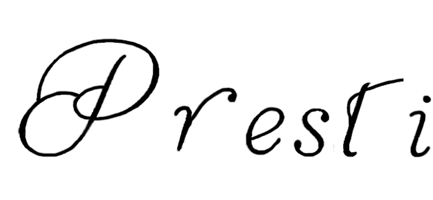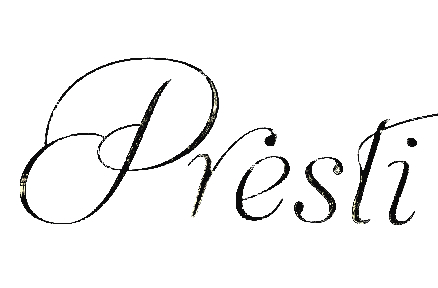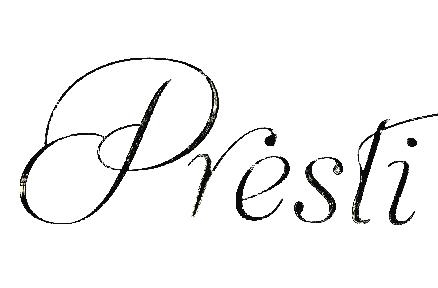
Bitte sagt mir, welche Schrift das sein könnte
ich habe vieles im Netz gefunden, aber eben nicht genau diese Art Schrift.
Kann mir jemand helfen?
[…] ich habe vieles im Netz gefunden, aber eben nicht genau diese Art Schrift.
Moin, sei mir nicht böse, aber Du hast völlig verkehrt gesucht.
Gerade bei verschlungenen Schriften verhaspelt sich Whatthefont und erkennt zusammenhängende Buchstaben nur bruchstückhaft. Mache Dir die Mühe (siehe meine Beispiel), die Buchstaben auseinanderzuziehen und besonders die Formen nachzuzeichnen (Auflösung etwas erhöhen, entstandene Grobheit weichzeichnen, etwas Pinselarbeit bei Unterbrechungen in feinen Strichen, Nachbelichter etc. ). Whatthefont dankt Dir meistens mit einem Ergebnis.